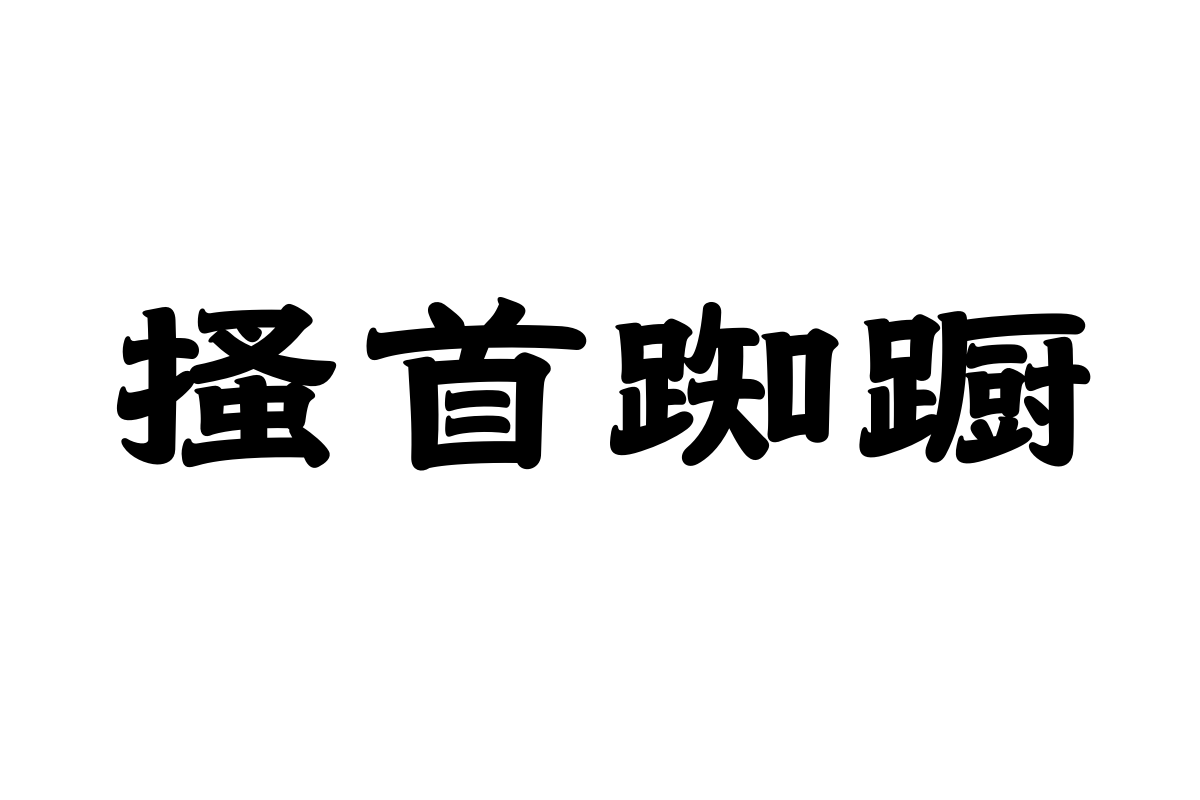
造字工房澄秋体是一款具有现代感和艺术感的字体,其特点包括:
1. 字形独特:造字工房澄秋体的字形设计独特,线条流畅,结构紧凑,给人一种简洁、明快的感觉。
2. 风格鲜明:该字体具有鲜明的个性和艺术气息,适用于需要突出个性和创意的设计场景。
3. 易于辨识:造字工房澄秋体在视觉上具有较强的辨识度,无论是在印刷还是电子屏幕上,都能清晰地展现其独特的魅力。
4. 适用范围广泛:该字体适用于广告、宣传、包装、网页、报纸等多种场合,具有较高的实用价值。
5. 支持多种字重:造字工房澄秋体提供了多种字重(如粗体、细体、斜体等),用户可以根据自己的需求选择合适的字重进行使用。
总之,造字工房澄秋体是一款具有现代感和艺术感的字体,适合用于需要突出个性和创意的设计场景,同时具备良好的实用性和广泛的适用范围。